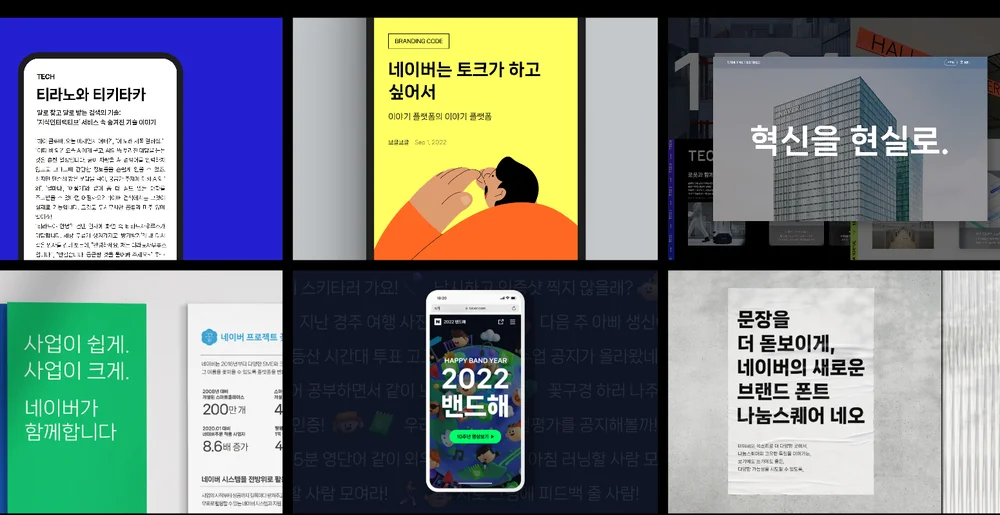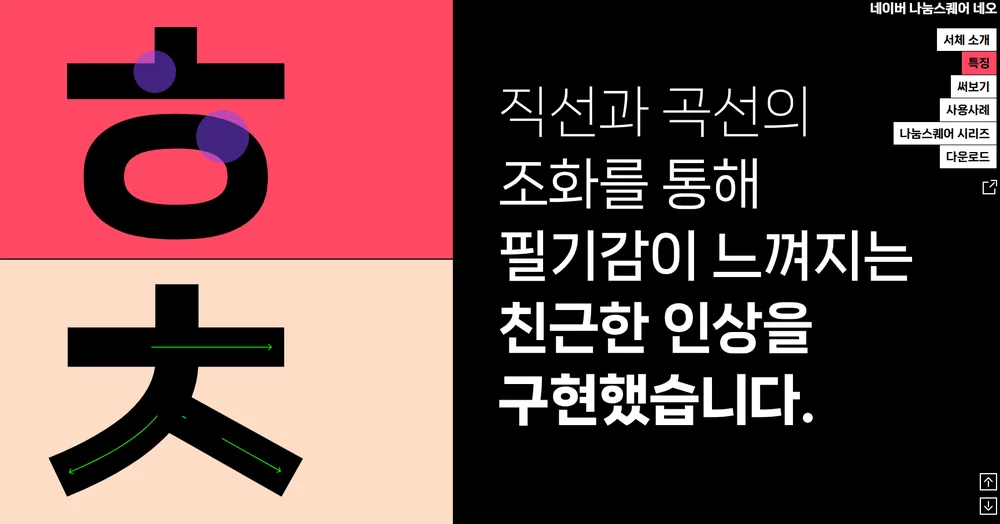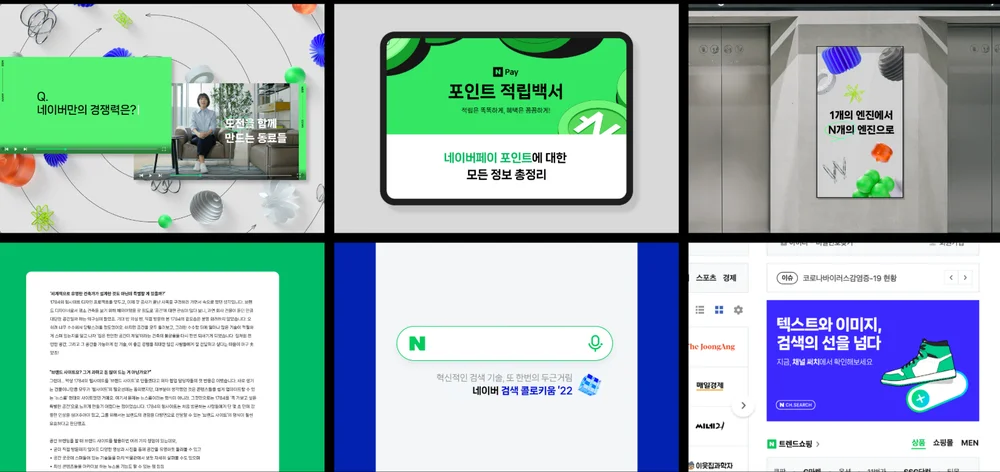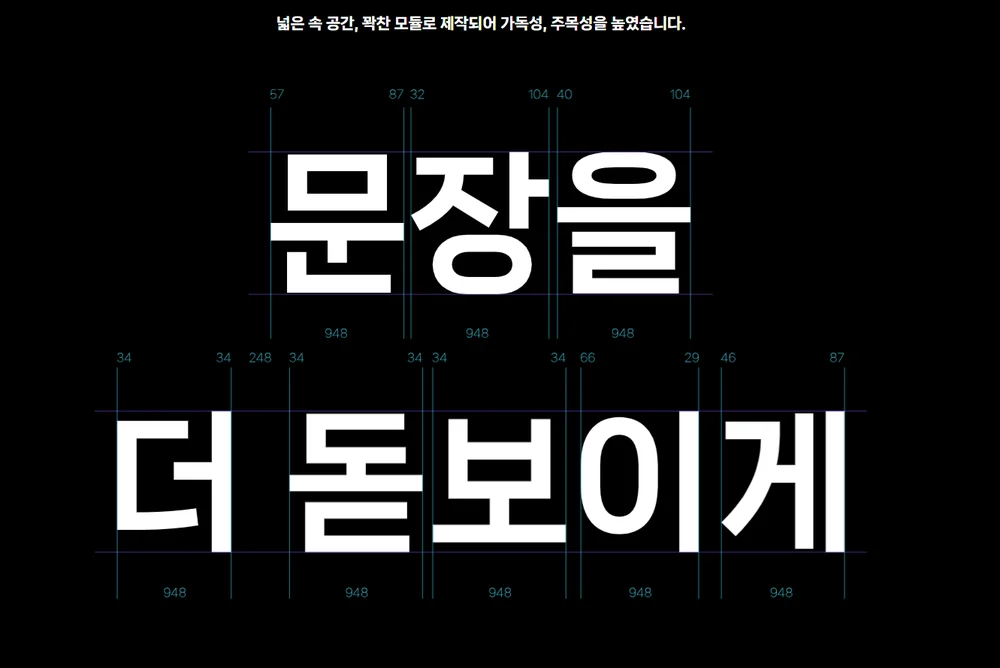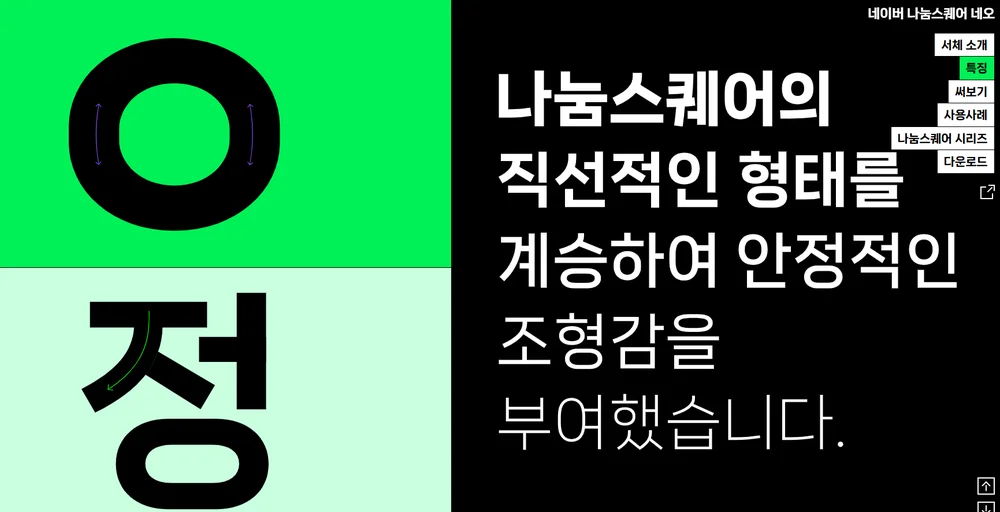
1. 나눔스퀘어 네오란? 🏛️
나눔스퀘어 네오는 네이버(NAVER)와 산돌이 공동으로 제작한 무료 한글 폰트입니다. 많은 분들이 이미 사용해 오셨던 '나눔스퀘어' 시리즈의 업그레이드 버전으로, 기존 나눔스퀘어의 깔끔하고 직선적인 느낌은 그대로 유지하면서도 직선과 곡선의 절묘한 조화를 통해 필기감이 느껴지는 친근한 인상을 더했습니다.
단순히 디자인만 바꾼 것이 아닙니다. 글자 수를 기존 나눔스퀘어의 2,350자에서 무려 11,172자로 대폭 확장하였고, 한글·영문·숫자의 밸런스를 정교하게 조정해 실용성을 크게 높였습니다. 또한 최신 폰트 기술인 배리어블(가변) 폰트를 지원하여 하나의 파일로 굵기를 자유롭게 조절할 수 있습니다.
2. 나눔스퀘어 네오 핵심 스펙 한눈에 보기 📊
항목 세부 내용
제작사 네이버(NAVER) · 산돌 공동 제작
지원 글자 한글 11,172자 / 라틴 96자 / 약물 967자(AK-9)
굵기(Weight) Light(300), Regular(400), Bold(700), ExtraBold(800), Heavy(900) — 총 5단계
가변 폰트 지원 (Variable Font)
3. 기존 나눔스퀘어와 무엇이 다를까? 🔍
나눔스퀘어를 이미 사용하고 계신 분들이라면 "굳이 네오로 바꿔야 하나?" 하는 의문이 드실 수 있습니다. 아래 비교표를 보시면 네오로 업그레이드해야 하는 이유가 명확해집니다.
항목 나눔스퀘어 (구버전) 나눔스퀘어 네오
한글 글자 수 2,350자 11,172자
굵기 단계 4단계 5단계 (Heavy 추가)
가변(Variable) 폰트 ❌ 미지원 지원
디자인 스타일 직선 강조 직선 + 곡선 조화
영문 밸런스 보통 수준 개선됨
웹폰트 최적화 부분적 WOFF2 완전 지원
특히 한글 글자 수가 5배 가까이 늘어난 것이 가장 큰 차이점입니다. 기존 나눔스퀘어는 자주 쓰이는 글자 위주로만 포함되어 있어서 드물게 쓰이는 한글 자모 조합은 폰트가 깨지는 경우가 있었지만, 네오 버전에서는 그런 걱정 없이 모든 한글을 완벽하게 표현할 수 있습니다.
4. 나눔스퀘어 네오 디자인의 특징 심층 분석 ✨
직선과 곡선의 조화
나눔스퀘어 네오 조형적 특징
나눔스퀘어 네오의 가장 큰 디자인 철학은 바로 '직선과 곡선의 공존'입니다. 기존 나눔스퀘어가 딱딱하고 정방형적인 느낌이 강했다면, 네오는 획의 끝 처리나 곡선 부분에 부드러움을 더해 더 친근하고 따뜻한 인상을 줍니다.
넓은 속 공간 설계
나눔스퀘어 네오 가독성 특징
한글 폰트 설계에서 '속 공간(내부 여백)'은 가독성에 직결됩니다. 나눔스퀘어 네오는 의도적으로 넓은 속 공간을 설계하여 작은 크기로 표시해도 글자가 뭉개지지 않고 명확하게 읽힙니다. 모바일 화면처럼 작은 디스플레이 환경에서도 탁월한 가독성을 보여주는 이유가 바로 여기에 있습니다.
친근한 필기감의 조형미
나눔스퀘어 네오 필기감 디자인
나눔스퀘어 네오는 직선과 곡선의 절묘한 조화를 통해 한층 부드러워진 조형미를 자랑합니다. 단순히 기하학적인 형태에 그치지 않고, 사람이 직접 쓴 듯한 자연스러운 필기감을 구현하여 사용자에게 더욱 친근하고 따뜻한 인상을 전달합니다.
8. 나눔스퀘어 네오가 잘 어울리는 상황 🎨
• 블로그 · 뉴스레터 본문: 긴 문단도 눈이 피로하지 않은 탁월한 가독성
• 카드뉴스 · 인포그래픽: 굵기 5단계를 활용한 시각적 위계 표현
• 모바일 앱 UI: 작은 화면에서도 명확하게 읽히는 속 공간 설계
• PPT · 프레젠테이션: Heavy 굵기의 강한 제목과 Light의 조화
나눔스퀘어 네오 사용 사례 1 나눔스퀘어 네오 사용 사례 2
나눔스퀘어 네오는 완전 무료, 상업적 이용 가능, 높은 가독성, 가변 폰트 지원이라는 네 가지 강점을 모두 갖춘 국내 최고 수준의 한글 폰트입니다. 아직 구버전을 사용 중이시라면 오늘 바로 네오로 업그레이드해 보세요! 😊